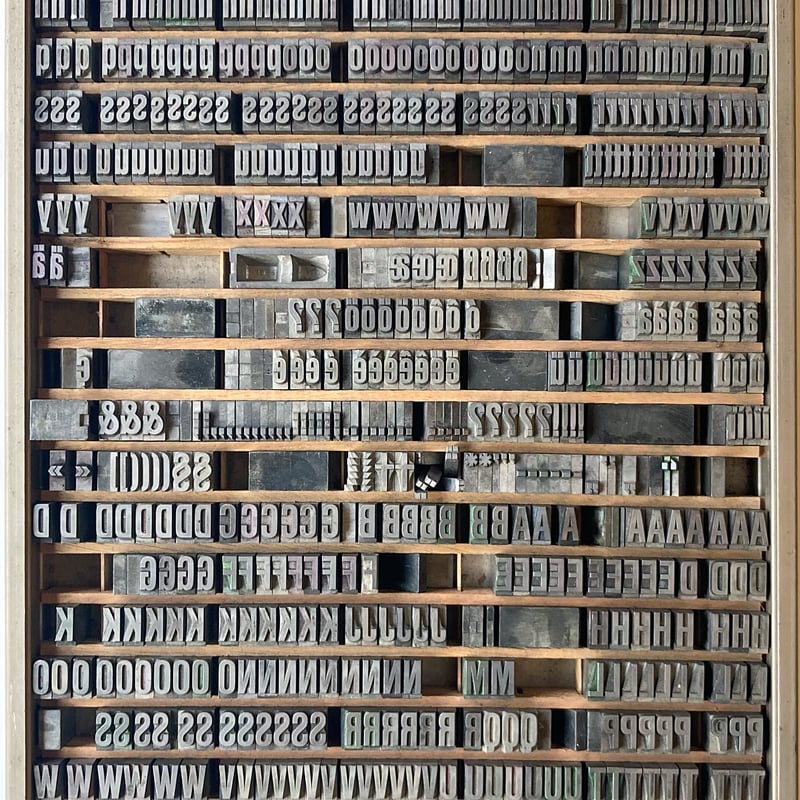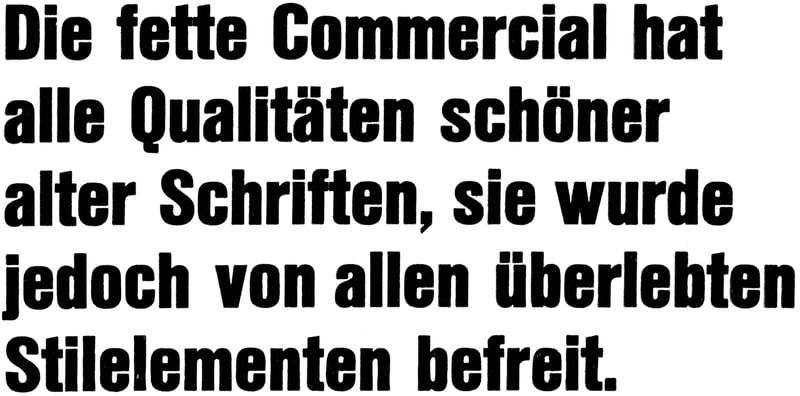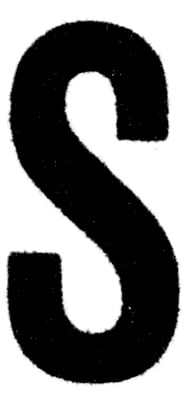
Commercial-Grotesk Semibold Condensed
Grösse: 36 pt
Druckmuster mit Text «Commercial-Grotesk, Halbfett, 36pt»
Klassifizierung
Slab Serif
Schriftschnitt
Semibold, Condensed
Grösse
36 pt / 3 c
Material
Metall
Design
Edmund Thiele
Jahr
1940
Schriftgiesserei
Haas
Die Commercial-Grotesk halbfett wurde von Edmund Thiele durch Abschneiden der Serifen seiner Superba (1935) entworfen und 1940 von Haas herausgegeben. Später ging sie als Helvetica schmalhalbfett, schmalfett bzw. Comerciale Compacte in die Helvetica-Serie über (1964).